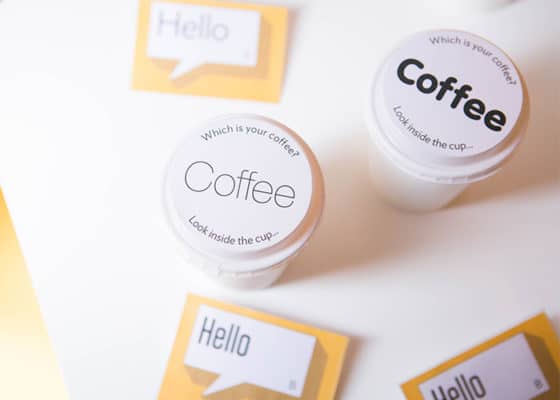
Was Fonts über Sie verraten: Type Tasting
Versteckt in voller Sicht umgibt Typografie uns überall – und für Marken ist die Verwendung des richtigen Fonts eine wichtige Form der Kommunikation.
Schrifttypen spielen ein große Rolle in unserem Alltag, aber meist bleiben sie an der Peripherie unseres Bewusstseins und beeinflussen unsere Entscheidungen, ohne unsere Aufmerksamkeit zu fordern.
Und laut Sarah Hyndman, Gründerin des Schriftstudios Type Tasting, ist es gerade diese Subtilität, die Typografie zu einem so wirkungsvollen Kommunikationsmittel macht.
MOO hat sich mit ihr unterhalten, um die erstaunliche Macht der Typografie aufzudecken – und herauszufinden, wie sie die Persönlichkeit Ihrer Marke zum Ausdruck bringen kann.
Weitergabe einer Leidenschaft
Als Kind war Sarah von der bunten Typografie auf den Verpackungen ihrer Lieblingssüßigkeiten fasziniert. Doch trotz dieser früh erblühten Begeisterung geriet ihre Liebe zur Typografie ins Wanken, nachdem sie 10 Jahre lang ihr eigenes Grafikdesign-Unternehmen geführt hatte.
„Ich kam an einen Punkt, an dem ich immer bis spät abends arbeitete, und meistens war es keine Designarbeit – ich habe nur die Accounts verwaltet“, sagt sie. „Also bin ich einen Schritt zurückgetreten, um etwas zu tun, das mir helfen würde, mich wieder ins Design zu verlieben.
Ich wollte die Begeisterung und Freude meiner Kindheit wiedererwecken und meine Liebe zur Typografie einem Publikum außerhalb des Designstudios nahebringen. Schrift ist nicht immer hochintellektuell – sie ist auch in der Popkultur verwurzelt.“ Und so kam es, dass Sarah vor fünf Jahren Type Tasting gründete.
Mit einem laserscharfen Fokus auf Typografie veranstaltet Type Tasting Events, Vorträge und Workshops, um Designer und Design-Neugierige mit der Psychologie von Schrifttypen vertraut zu machen – es sei wie eine Weinprobe, nur für Typografie, erklärt Sarah.
Sie hat außerdem ein Buch mit dem Titel Why Fonts Matter veröffentlicht, das untersucht, wie Fonts uns beeinflussen und was für eine subtile Macht sie ausüben. Sie können sogar unseren Essensgeschmack beeinflussen, sagt Sarah.
„Wenn ein Menü oder Rezept in einer Serifenschrift geschrieben ist, wird der Koch als kompetenter wahrgenommen und das Rezept als besser schmeckend empfunden“, erklärt Sarah. „Der Sinn hinter Type Tasting ist, Schrift auf diese Weise zu betrachten, aus der Sicht des Verbrauchers.“
Entdeckung einer verborgenen Welt
Type Tastings praktische, experimentelle Events sind darauf ausgerichtet, die faszinierenden Facetten einer Welt, die Sarah als „versteckt in voller Sicht“ beschreibt, für alle zugänglich zu machen.
Zu den angebotenen Events gehört eine Type Safari, bei der die Teilnehmer durch die Geschichte der Schrift geführt werden, um ihnen zu zeigen, warum verschiedene Schriftarten relevant sind.
Type & Perception umfasst ein ,Typografie-Karaoke’, das demonstriert, „wie Schrift Ihre Stimme sein kann“, während Font Fortunes enthüllt, was Ihre bevorzugten Schriftarten über Ihre Persönlichkeit aussagen.
Die Resonanz auf diese Veranstaltungen war enorm positiv. „Die Teilnehmer sind überrascht von den Sessions und es gibt viel Gelächter“, sagt Sarah. „Leute, die dachten, dass sie nichts über Schrift wissen, entdecken, dass sie bereits Experten darin sind, diese visuellen Codes zu lesen.“
Die subtile Stimme der Schrift
Sarah versteht besser als die meisten, welchen Einfluss Typografie auf unsere Wahrnehmung haben kann und warum es sie zu einem wirksamen Markenbildungstool macht.
„Schrift ist unsere Stimme, also reflektiert die Schriftart, die Sie nutzen gewissermaßen Ihre Persönlichkeit“, erklärt sie. „Sie vermittelt einen ersten Eindruck, auf ganz ähnliche Art wie unsere Kleidung. Wenn ich zum Beispiel etwas in Serifenschrift setze, ist es, als würde ich meine Brille aufsetzen – es hat sich gezeigt, dass Menschen Wörter in Serifen als gut recherchiert und intellektuell interpretieren.“
Jedes Detail von Type Tasting, bis hin zu Sarahs Visitenkarten, basiert auf ihrer Leidenschaft für Typografie und Design.
„Ich habe Luxe für meine Visitenkarten gewählt, teilweise wegen des Farbstreifens entlang der Naht, aber auch, weil sie schwer sind“, sagt sie. „Je schwerer das Objekt, desto mehr Gravitas hat es und desto wichtiger fühlt es sich an, wenn man es hält.
Meine Visitenkarten haben außerdem ein eingebautes Spiel, das erklärt, was ich mache – effektiv ist es mein Elevator Pitch – damit sie zum Gesprächsthema werden. Jemand hat kürzlich gesagt, dass ein Visitenkarten-Designer im Grunde genommen ,richtig coole erste Eindrücke’ kreiert, und genau das habe ich angestrebt.“
Typografie, die eine Geschichte erzählt
Also, welchen Rat würde Sarah einem kleinen Unternehmen oder einer Marke geben, die ihr Image verbessern wollen?
„Denken Sie über Ihre Marke und die Geschichte nach, die Sie erzählen wollen, um eine authentische und bedeutungsvolle Verbindung zu Ihren Kunden aufzubauen“, rät Sarah. „Ihr Branding sollte Ihre Persönlichkeit oder Einstellung reflektieren – seriös und gut informiert, offen und modern oder locker und lässig.
Es könnte eine Geschichte oder Ära evozieren – die Cooper Black Schriftart sagt z.B. ,70er Nostalgie und Sonnenschein’, während Benguiat ,authentisch 80er’ sagt (denken Sie an Stranger Things). Sie können es auch nutzen, um mit einer bestimmten Gruppe zu kommunizieren, indem Sie Schriftarten und den Tone of Voice nutzen, die Sie Ihrer Zielgruppe nahebringen.“
Sarah nennt Coca Cola und Pepsi als starke Beispiele für Schriften, die die Werte einer Marke verkörpern.
„Cokes lässiger Schriftzug reflektiert das Erbe der 50er Jahre. Es ist ein Getränk für jedermann, das Baseball und Amerikana evoziert. Pepsis Logo dagegen reflektiert die Mode der jeweiligen Ära und steht eher für Popkultur und Wandel.“
Wenn Type Tasting den Menschen einen Einblick in die Kunst und Psychologie der Typografie und Wertschätzung dafür vermitteln kann, betrachtet Sarah ihre Mission als erfüllt.
„Typografie ist eins der wichtigsten Mittel, um einen ersten Eindruck zu machen und Ihre Geschichte zu kommunizieren“, sagt Sarah.
„Selbst isoliert betrachtet kommuniziert der Schriftstil einer Marke eine gewaltige Menge. Es geht nicht um das Kerning – es geht um den Eindruck, den Typografie auf unser Unterbewusstsein macht.“